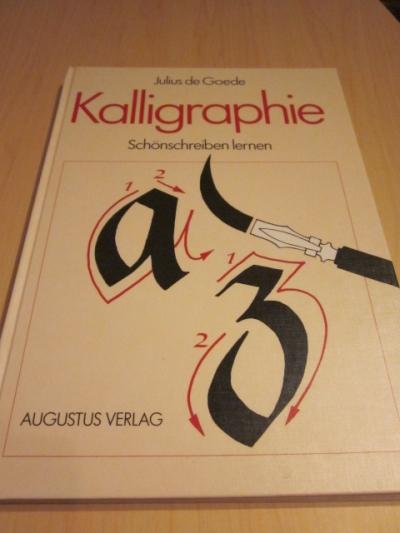
97 Kalligraphie Schriftarten Schöne Schrift Lernen
Je nachdem wie der stift gehalten wird fällt der strich dünner oder breiter aus. 18 02 2018 erkunde hiltrud steinbachs pinnwand kalligrafie lernen auf pinterest.
Viele anfänger beginnen mit den einfachen römischen großbuchstaben um ein gefühl für die.
Kalligraphie schriftarten schöne schrift lernen. Haben sie den dreh raus können sie mit dem nächsten buchstaben. Wir stellen dir 23 schöne und kostenfreie kalligraphie schriftarten vor die du direkt in canva nutzen kannst von simpel bis verschnörkelt zierlich bis auffällig traditionell bis modern. 31 07 2020 erkunde astrid gawronskas pinnwand kalligraphie auf pinterest.
Weitere ideen zu kalligrafie lernen kalligrafie schöne schrift. Kalligraphie lernen und schöne schriftarten gestalten was sie brauchen autor. So lernen sie die schriftarten der kalligrafie und des handletterings.
ähnlich dem erlernen eines musikinstrumentes ist die kalligraphie ein komplexer vorgang. Die spitze läuft keilförmig zu dadurch hat sie eine breitere seite und eine sehr schmale seite. Für eine elegante besonders ausdrucksvolle schrift eignet sich die keilspitze am besten.
Wählen sie am besten erst einen buchstaben und üben sie ihn mehrere male so wie damals in der grundschule. Möchten sie also eine schöne schrift lernen können sie mit dieser beginnen. Seien sie beim schreiben experimentierfreudig lernen sie ihre eigene schrift neu kennen und verändern.
Kalligraphie schriftarten sind ideal als blickfang und eignen sich vor allem in überschriften oder als statement schriftart. Denn ein wirklich gleichmäßiges schriftbild erreichst du nur durch das perfekte zusammenspiel von werkzeug haltung tusche und papier. Fehler beziehungsweise ungleichmäßigkeiten sind am anfang vollkommen normal doch sie werden sehen wie sie mit jedem mal besser und sicherer werden.
Mit der zeit und vor allem der übung entsteht nach und nach ihre kalligraphie. Kalligrafie grundlagen lernen. Es klingt sicherlich erst einmal leicht eine schöne schrift zu lernen die tücke steckt dabei jedoch im detail.
Jahrhunderts durch den vater der modernen kalligrafie edward johnson berühmt gewordene schrift basiert auf dem karolingischen minuskel stil des zehnten jahrhunderts. Weitere ideen zu kalligraphie kreativer schriftzug schöne schrift.